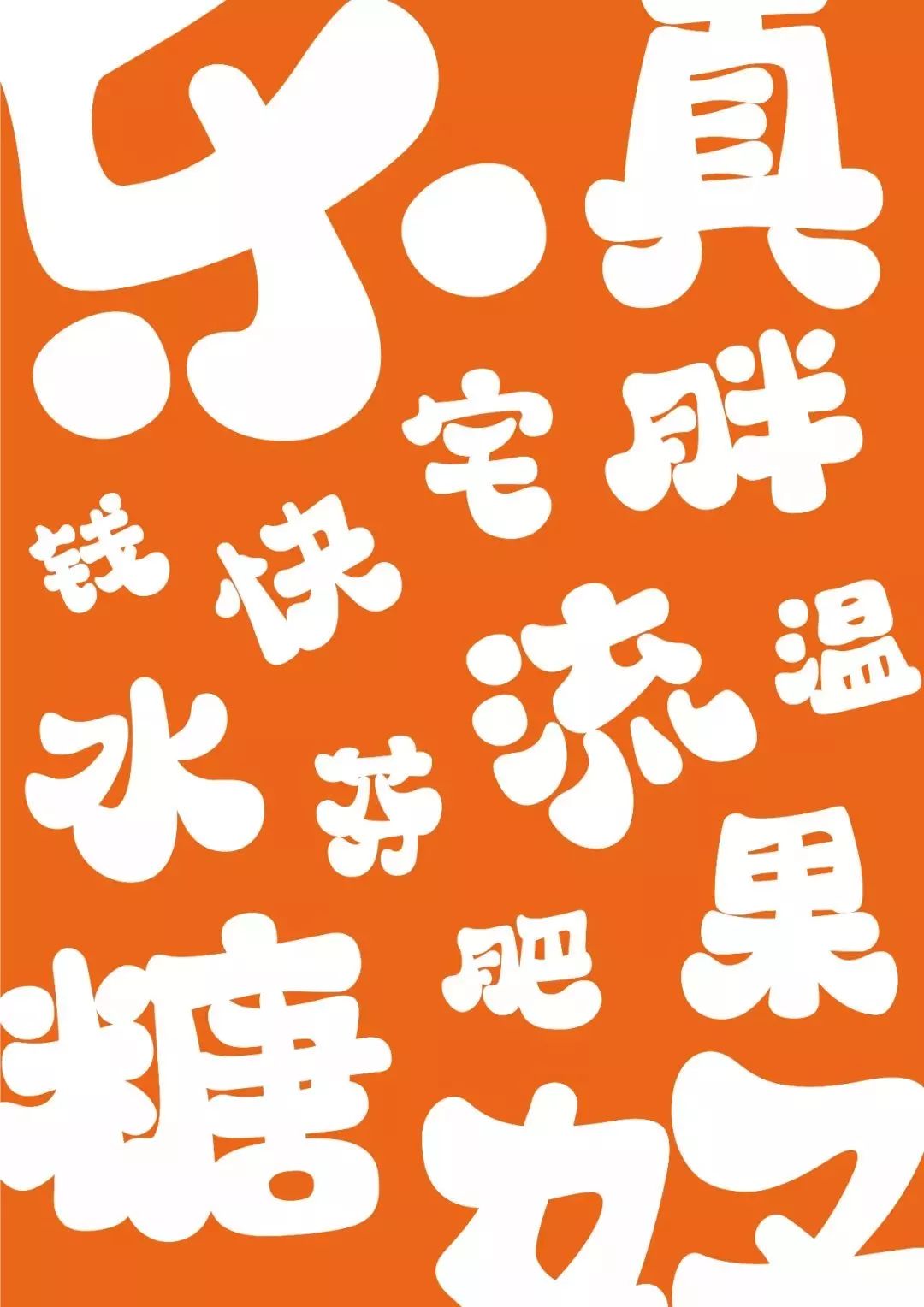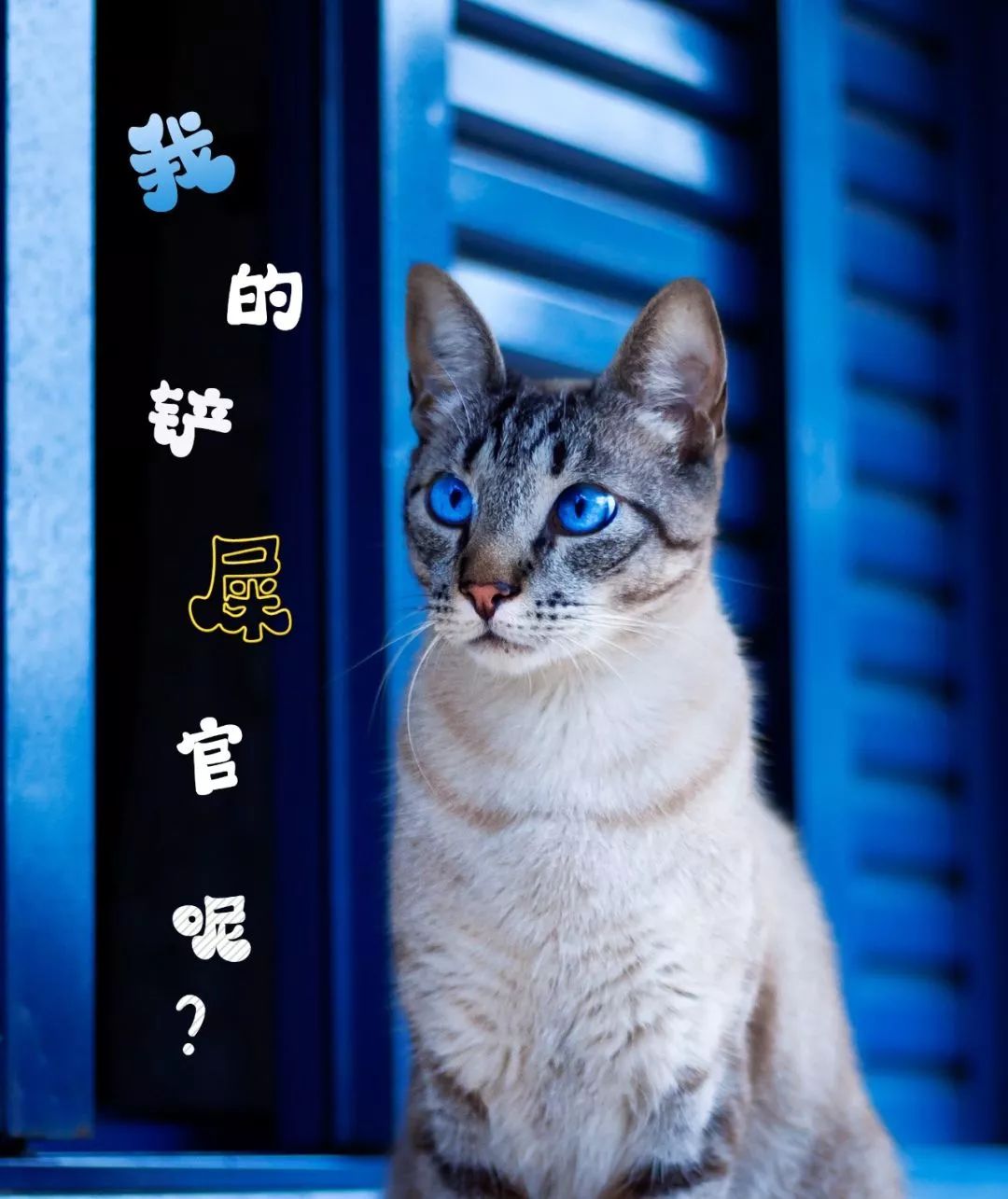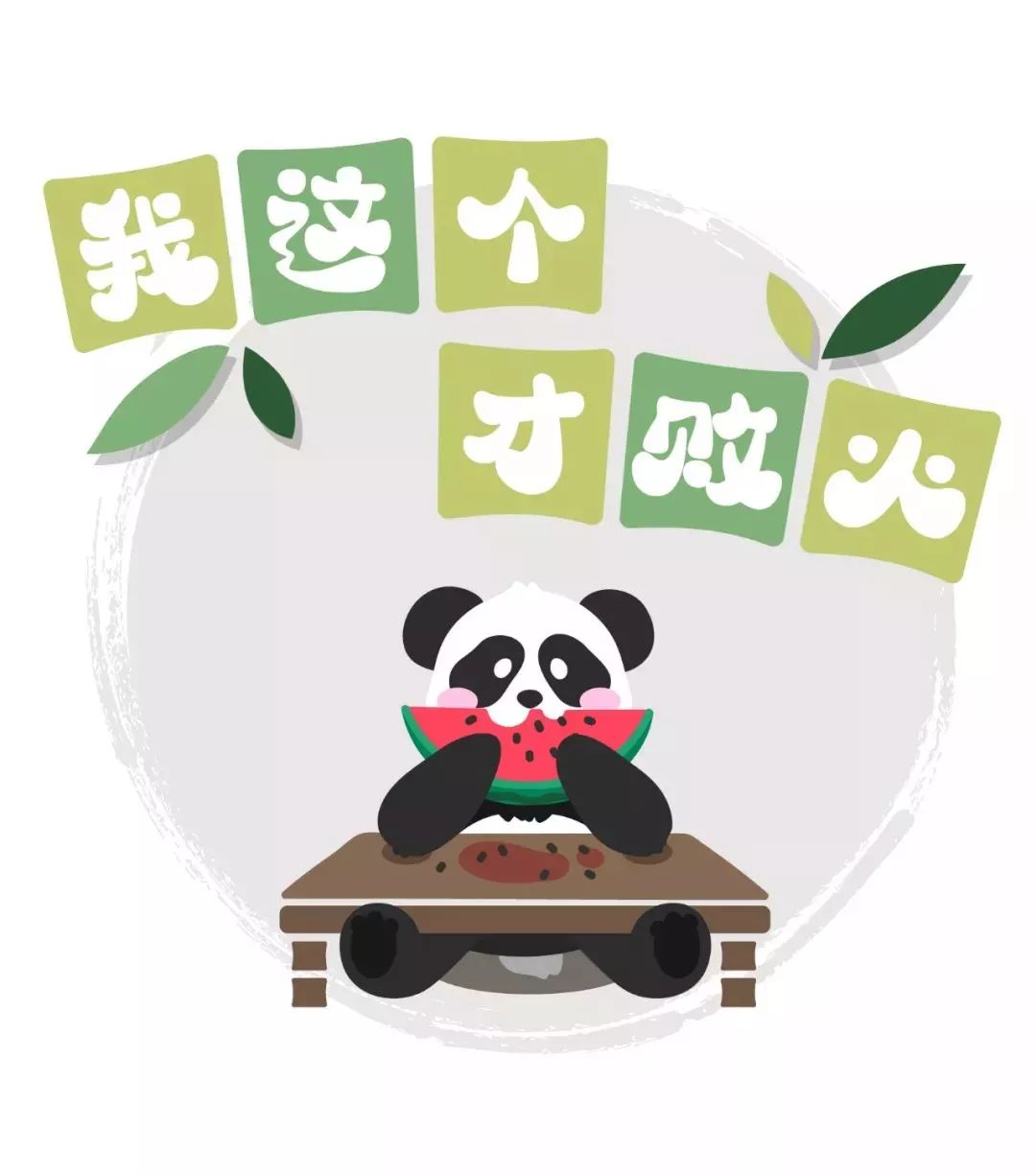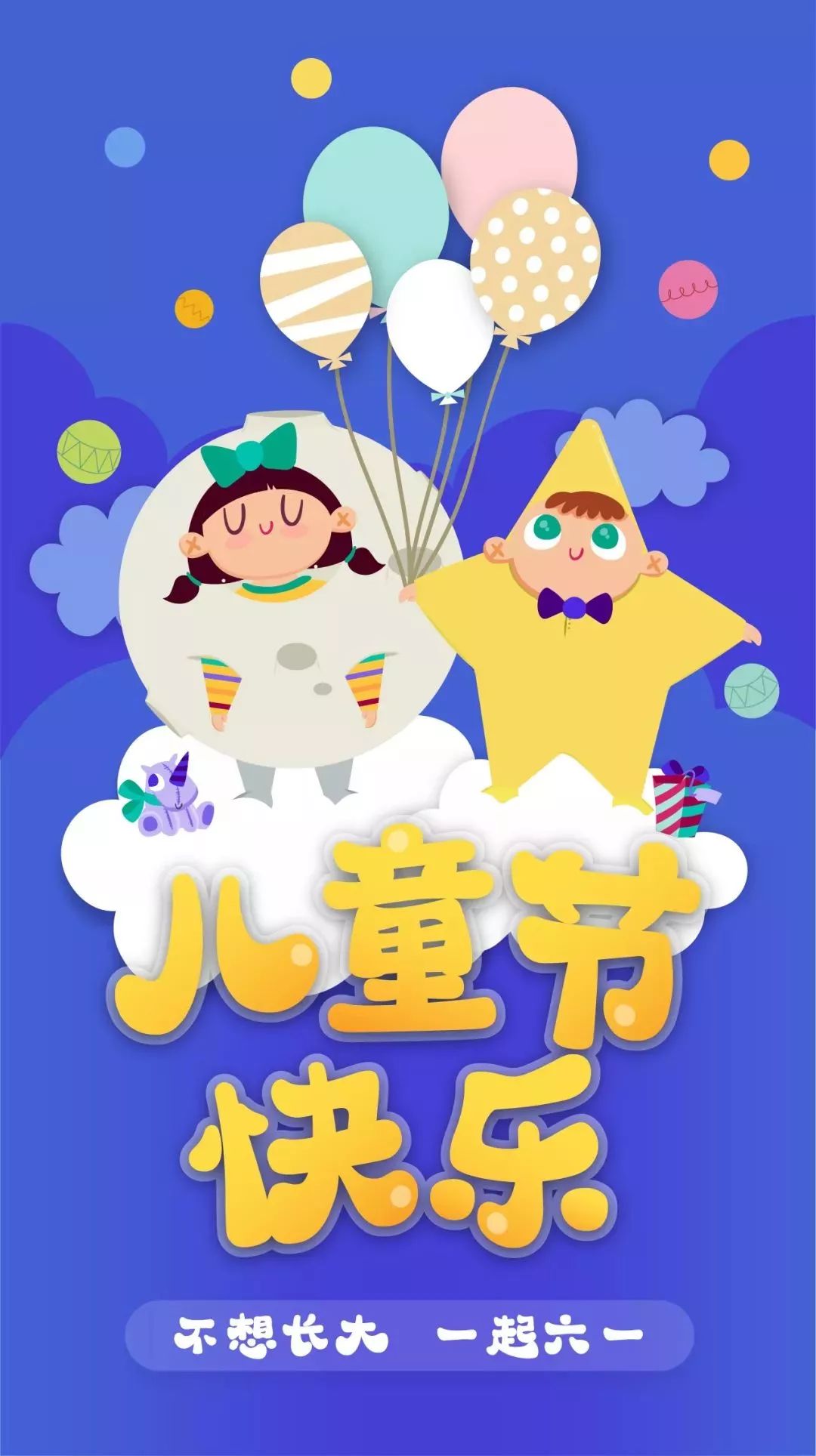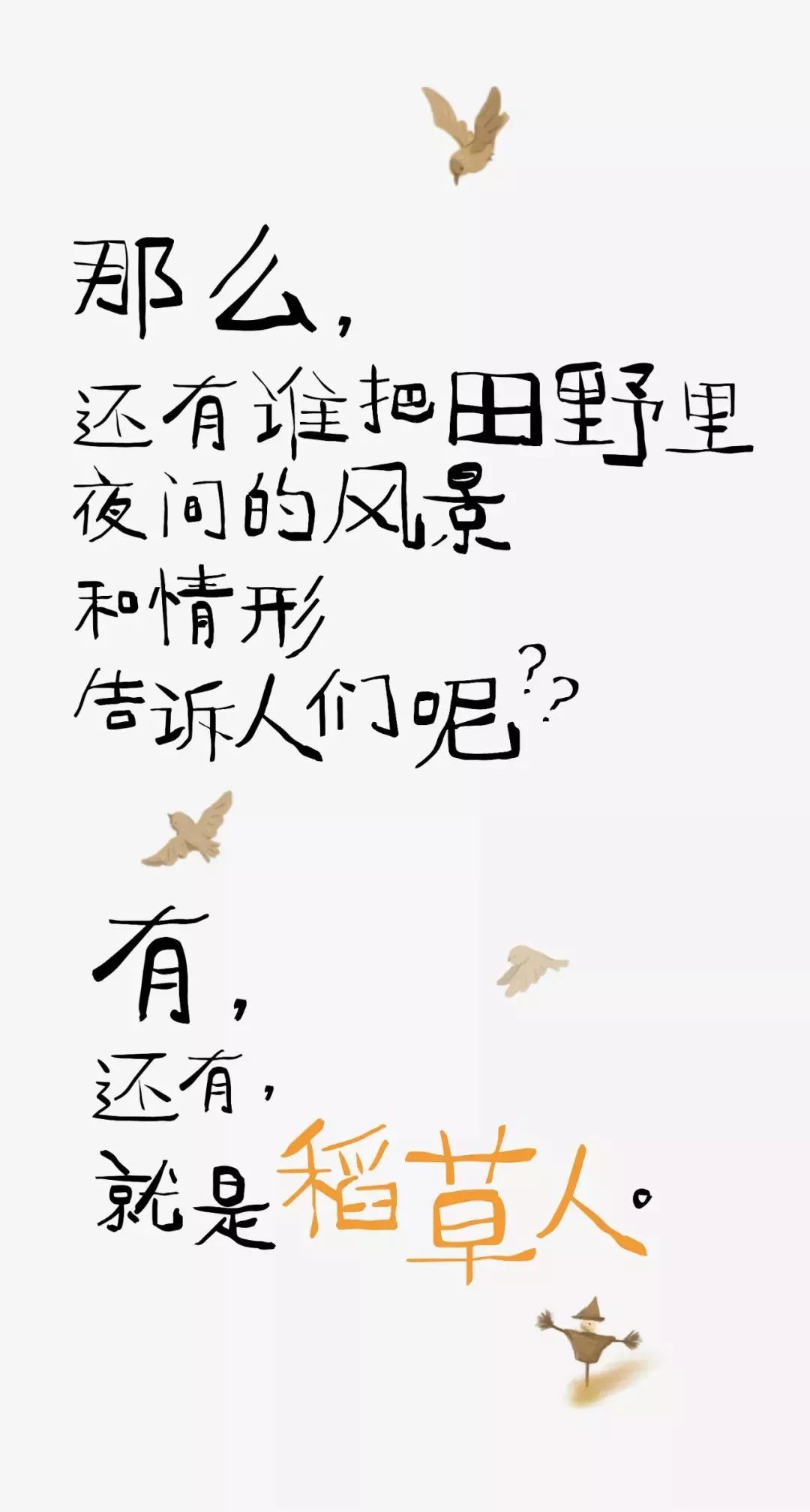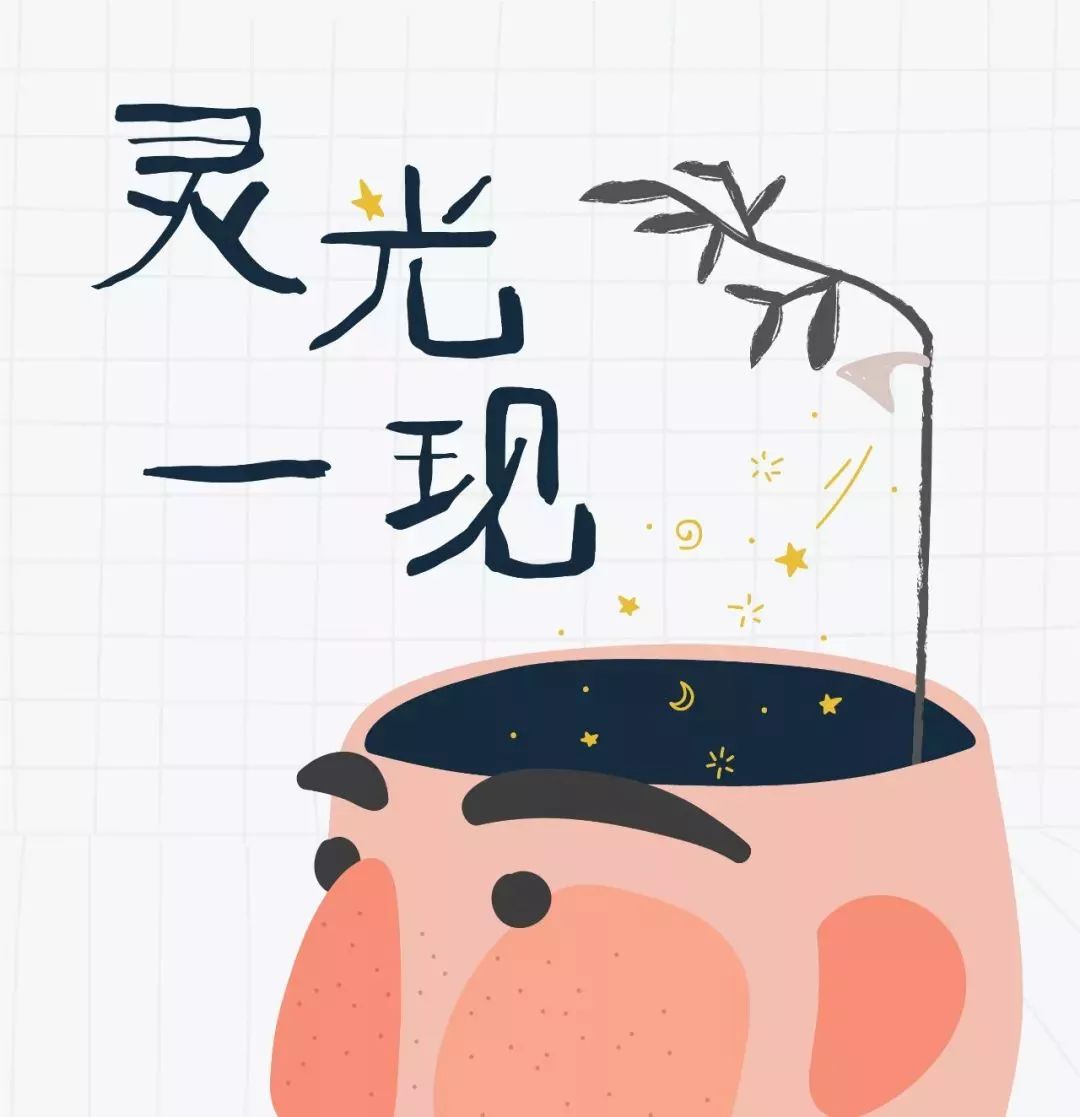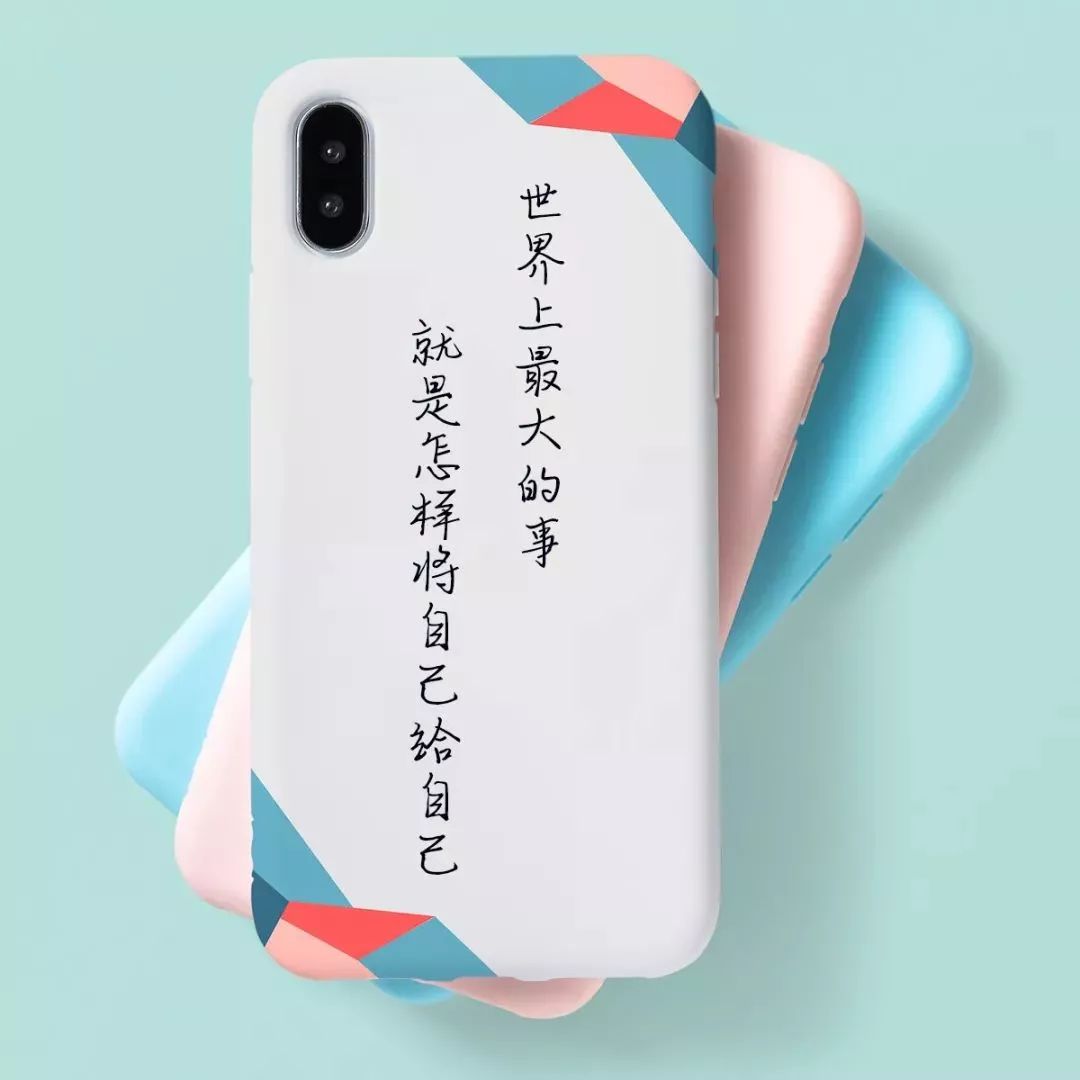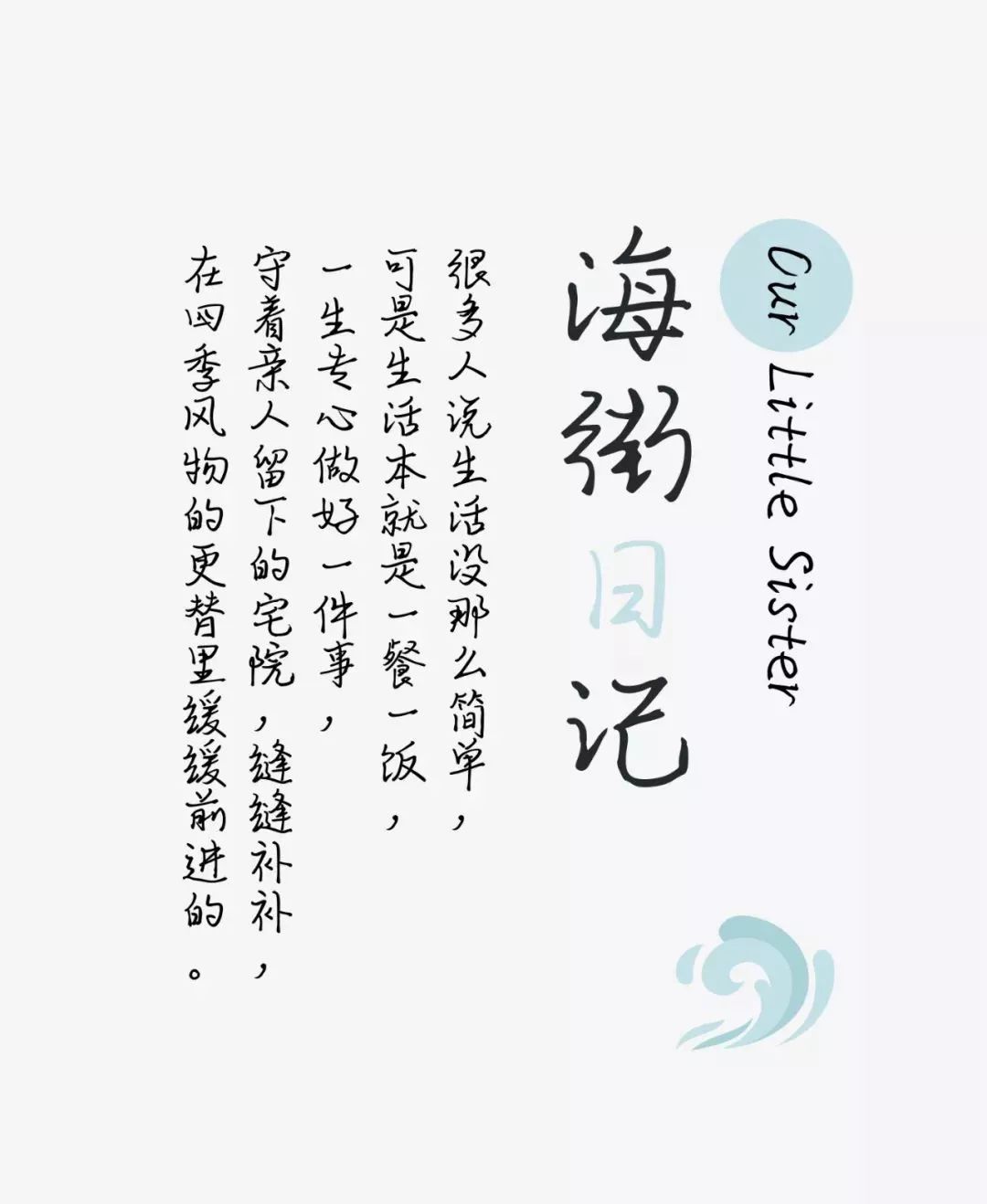
中文的来自点字库,一个年轻的字体品牌,先来看看它的自我介绍~
点字QQ糖
首先登场的是我们的萌系字体——点字QQ糖,立马想起了童年有木有~
它的特点也是Q弹软糯、温润可爱、亲和有趣,看完就想咬一口~
来看看细节,偏旁部首大小错落有致、灵活搭配,突显字体的趣味性。
“口”笔形+不规则圆形,使这款字体更加活泼生动。
粗细变化增加了字体的手写感,有几分俏皮。
笔画弧度流畅,风格统一,圆咕隆咚~有没有让你想起某个人!
实际应用上,它也有很多种打开方式~
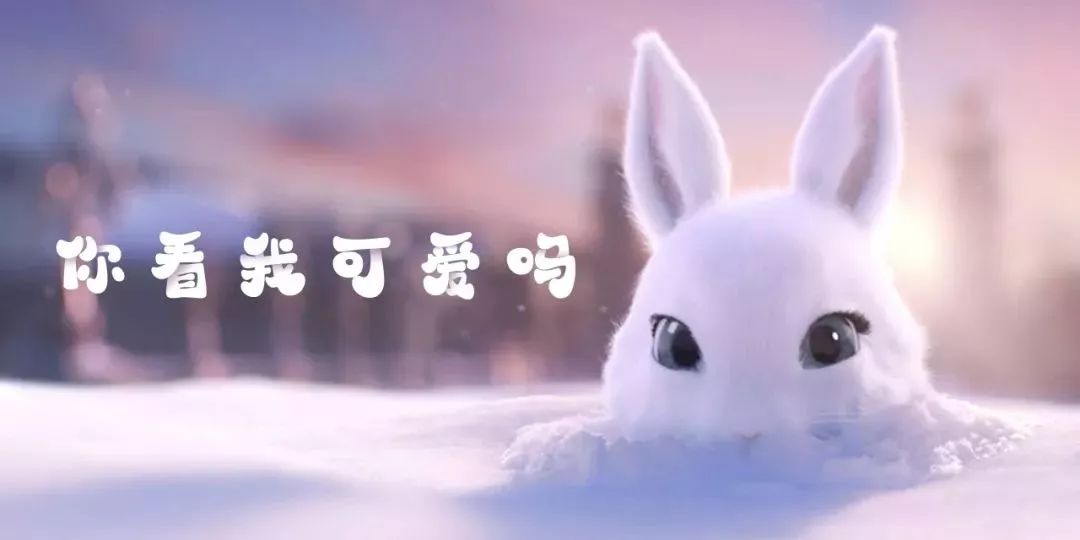
点字稻草人
第二个隆重登场的是一款个性字体——点字稻草人。
它最大的特点就是淳朴、怀旧,还带着点乡村气息~
笔画线条生动多变,为字形增添不少趣味。
通过笔形自身粗细的对比,展现了稻草的糟乱之感。
略微靠下的视觉重心,让字体更加稳重。
夸张的字体结构,让笔画间显灵动活泼。
你可以用它表达文艺气质~
也可以用它表达可爱、佛系的个性~
点字晨颜行楷
最后一款是手写体,叫点字晨颜行楷,让你重拾记忆中的温暖时光~
它温暖、不拘一格,既有楷体的端正,又像少女的初恋。
不仅是手写感,端午、高考合体日,它也很合适表达情怀~
除了点字库,字由会员还上线了两款西文,来自3type,一个是Ellenda~
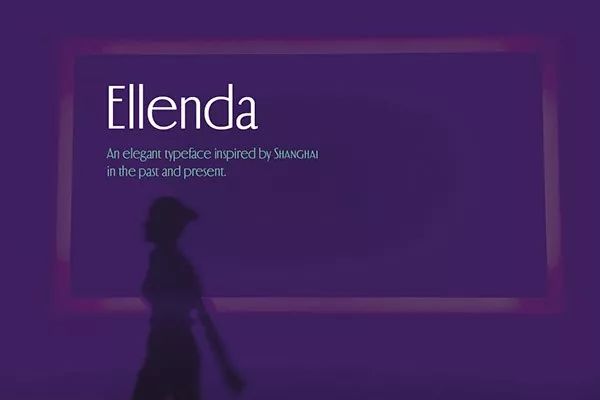
另一个是Ryan Serif~
它有三个家族字体,分别是light、Semilight、regular。